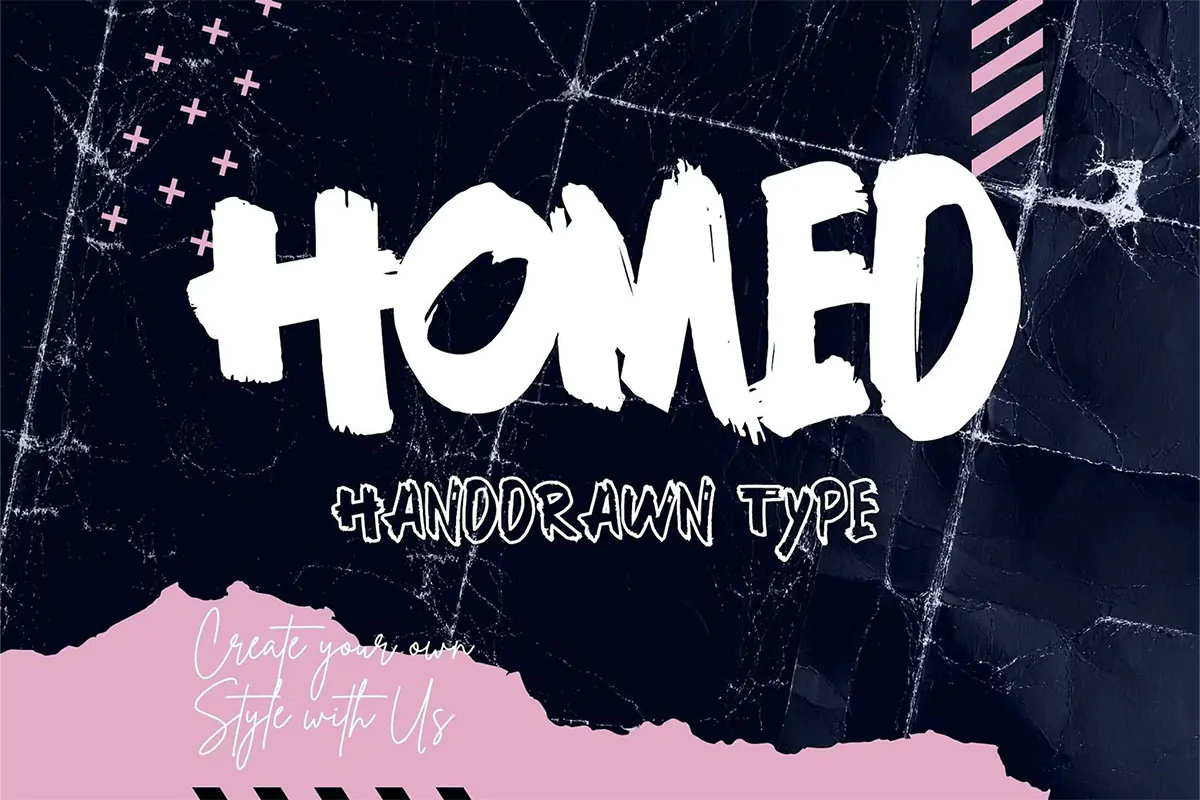
براش فونت دستنویس Homed
براش فونت دستنویس
براش فونت دستنویس Homed یک اسکریپت فونت زیبا است که به سبک قلمویی طراحی شده است و مناسب برای استفاده در طراحی پوستر، کارت ویزیت، بنر، تبلیغات، بسته بندی محصولات، ظروف یکبار مصرف و … می‌باشد.